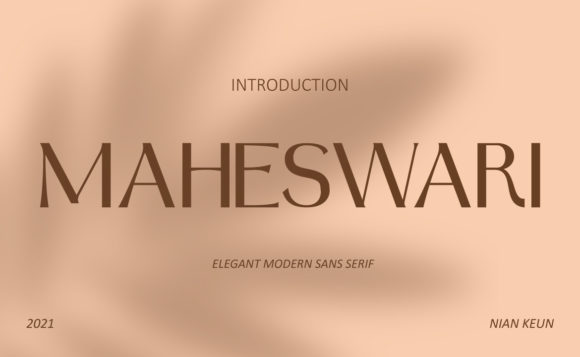
Название: Maheswari Font (2021)
Maheswari - классный, современный и аутентичный шрифт без засечек.
Этот универсальный шрифт имеет широкий спектр применения - от поздравительных открыток до заголовков.